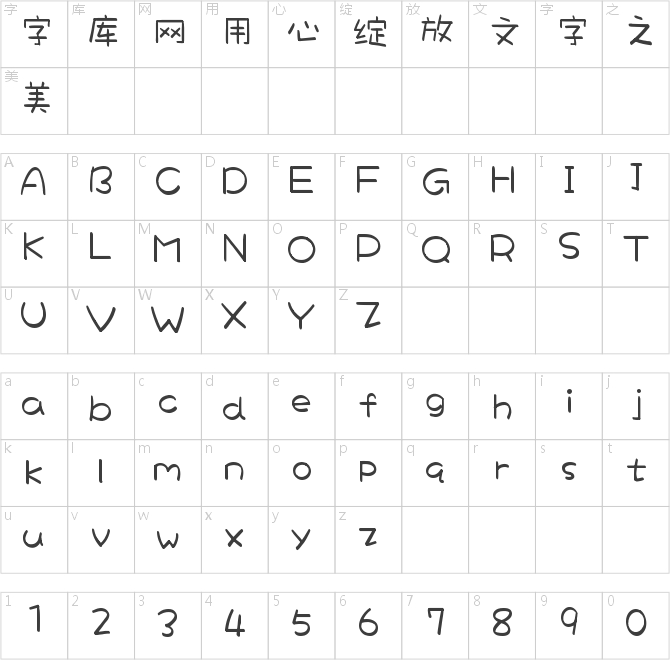
刺客伍六七-小飛雞字體下載文道刺客伍六七-小飛雞
刺客伍六七-小飛雞字體文道刺客伍六七-小飛雞字庫是一款讓人賞心悅目、百看不厭的中文字體,適合各類廣告和產(chǎn)品包裝設(shè)計應(yīng)用,字體大小5.53MB,格式為ttf字體,上傳用戶是文道字庫,作者/版權(quán)方為文道字庫